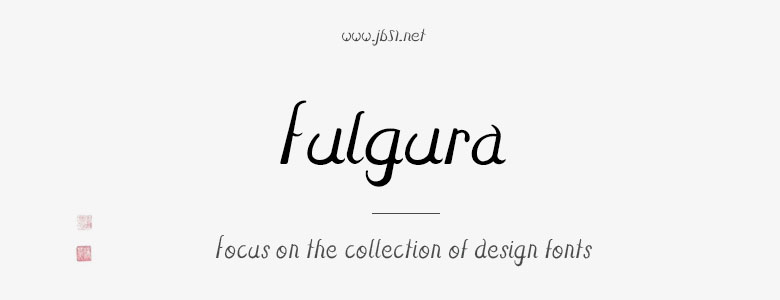
Fulgura英文手寫(xiě)字體,字體筆觸略細(xì),書(shū)寫(xiě)流暢,具有很好的視覺(jué)感,適合應(yīng)用于藝術(shù)設(shè)計(jì)、平面宣傳設(shè)計(jì)、網(wǎng)頁(yè)設(shè)計(jì),書(shū)法字帖等領(lǐng)域。有需要的朋友快來(lái)本站下載使用吧。